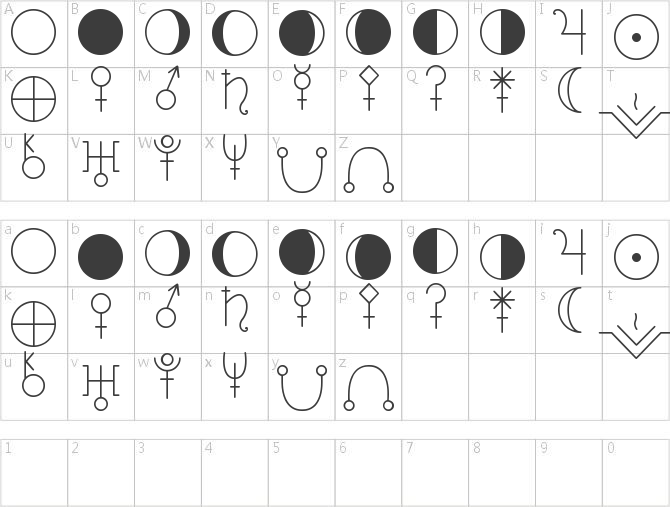
ASTOLOGY ASTROLOGICAL TFB
ASTOLOGY ASTROLOGICAL TFB字體字庫是一款讓人賞心悅目、百看不厭的英文字體,適合各類廣告和產(chǎn)品包裝設(shè)計應(yīng)用,字體大小0.01MB,格式為ttf字體,上傳用戶是13226568769,作者/版權(quán)方為未知